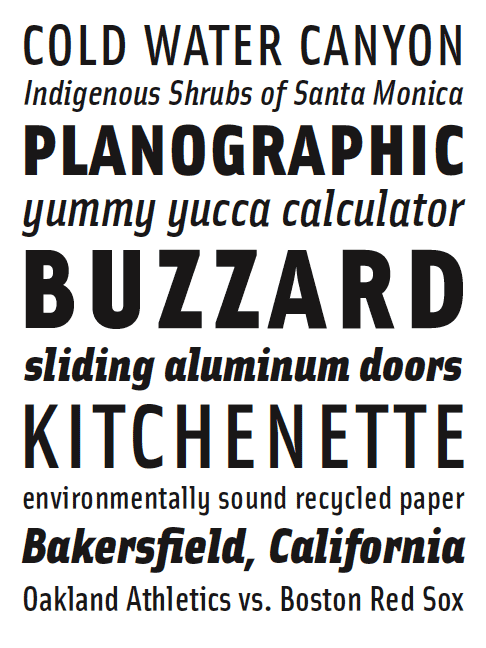
Serifenlose für Fließtext
Ich suche eine moderne serifenlose Schrift, die gut lesbar für Fliestext verwendet werden kann. Wichtig ist auch, dass die Schrift möglichst eng läuft, um viele Zeichen auf eine Seite zu bekommen ;-)
Hat jemand eine Idee/Anregung?